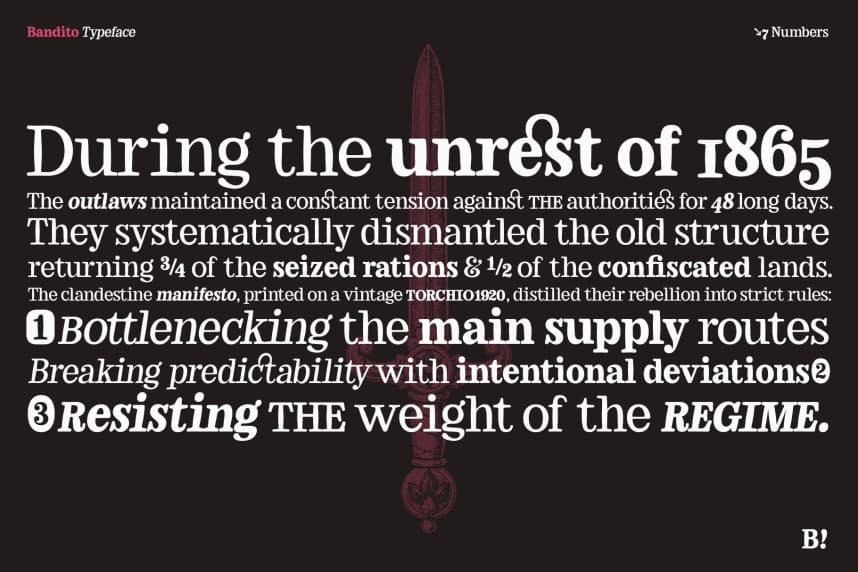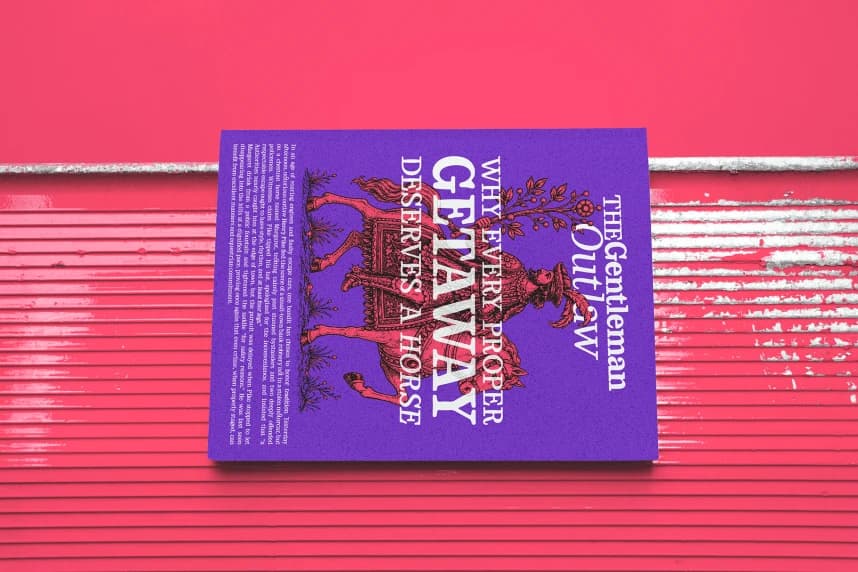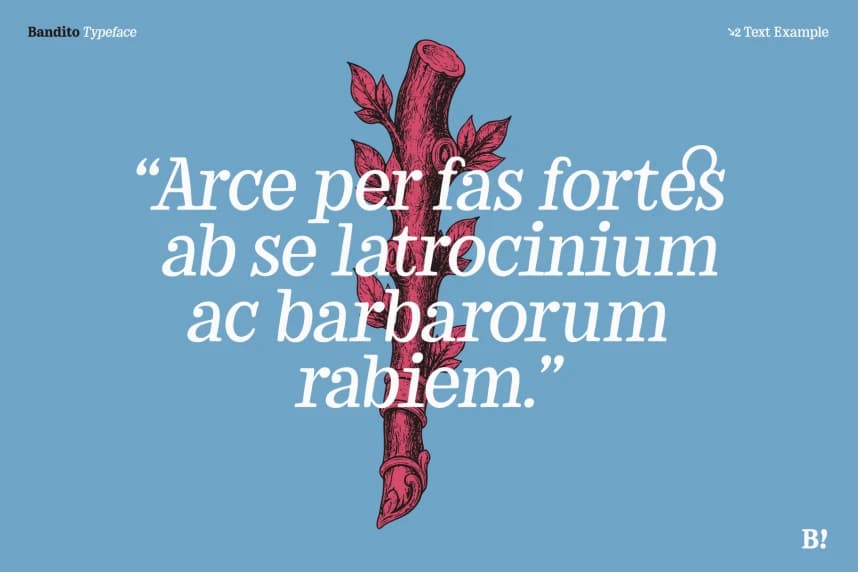
Bandito – Değişken Serif Yazı Tipi
Bandito - Variable Serif Typeface, çağdaş, yuvarlak hatlı bir serif yazı tipidir ve İtalyan tipografisinin sıcaklığı ve canlılığından kök alır. Eski posterlerden ilham alan ve güçlü ifade gücüne sahip bir grafik geleneğine dayanır.
Bandito - Variable Serif Typeface, İtalyan tipografisinin sıcaklığı ve canlılığından beslenen çağdaş, yuvarlak bir serif yazı tipidir. Eski afişlerden ilham alan ve güçlü ifade gücüyle öne çıkan bir grafik geleneğine sahiptir.
Bandito – Variable Serif Typeface